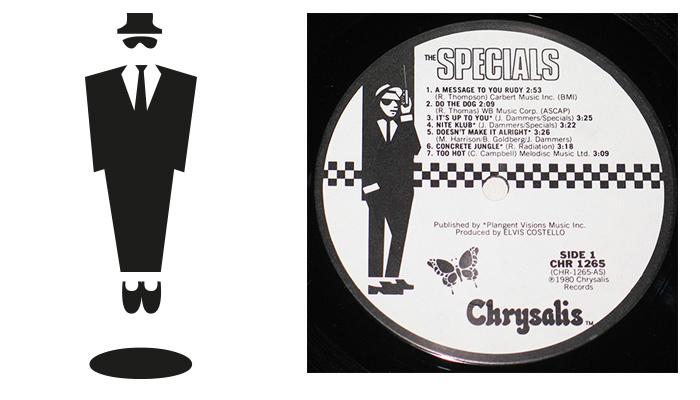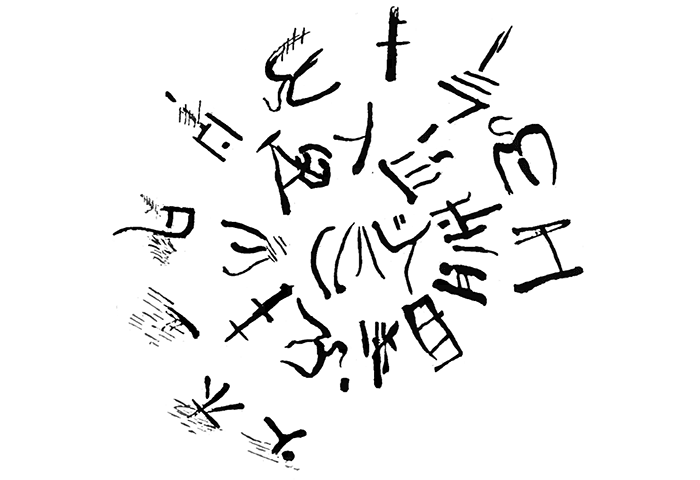
Vier Jahre nach der letzten Hauptversion erscheint mit der Version 7.0 nun eine weitere große Erweiterung des Schriftzeichen-Standards Unicode, die 2834 neue Zeichen mitbringt und den Gesamtumfang der kodierten Zeichen damit auf 113.021 Zeichen erhöht. Einige der neuen Bildzeichen in Unicode 7.0 sorgen in der Berichterstattung für Erheiterung. Zu diesen Zeichen zählen zum Beispiel:
»Stinkefinger« U+1F595
REVERSED HAND WITH MIDDLE FINGER EXTENDED»Vulkanier-Gruß« U+1F596
RAISED HAND WITH PART BETWEEN MIDDLE AND RING FINGERS»Schwebender Geschäftsmann« U+1F574
MAN IN BUSINESS SUITE LEVITATING
Die Auswahl solcher Zeichen wirkt auf Außenstehende nicht selten verwunderlich oder gar willkürlich. Doch hinter der Aufnahme neuer Zeichen stehen langwierige Abstimmungs- und Entscheidungsprozesse unter der Mitwirkung von Wissenschaftlern und nationalen und internationalen Normungsinstituten.
Der schwebende Geschäftsmann hat es übrigens lediglich aus Kompatibilitätsgründen in den Unicode geschafft. Die weit verbreiteten Piktogramm-Fonts Webdings und Wingdings wurden in den Unicode aufgenommen und damit auch der im Webdings-Font enthaltene, »schwebende Geschäftsmann«, der laut Aussagen der Zeichnerin Jen Sorenson eine Art Ausrufezeichen angelehnt an Plattencover der Band The Specials darstellen soll.
Neben weiteren Bildzeichen und neuen Währungszeichen für Rubel und den Aserbaidschan-Manat wurden auch 23 neue Zeichensysteme aufgenommen: Altnordarabische Schrift, Altpermische Schrift, Bassa-Schrift, Duployé-Kurzschrift, Elbasan-Schrift, Grantha-Schrift, Kaukasisch-Albanische Schrift, Khojki-Schrift, Khudabadi-Schrift, Linearschrift A, Mahajani-Schrift, Manichäische Schrift, Mende-Schrift, Modi-Schrift, Mro-Schrift, Nabatäische Schrift, Pahawh Hmong, Palmyrenische Schrift, Pau Cin Hau, Psalter Pahlavi, Siddham, Tirhuta und Warang Citi.
Mit 23 neuen Schriftsystemen ist dies die größte Anzahl neuer Systeme, die in einer Unicode-Version hinzugefügt wurden. Unicode 1.0 startete 1991 mit 24 Schriftsystemen. Die Erfassung aller Schriftzeichen der Welt wird also weiterhin konsequent vorangetrieben, auch wenn in der Berichterstattung der Fokus oft auf Piktogrammen bzw. Emoji liegt.
Die Linear-Schrift A der minoischen Kultur Kretas ist nun auch im Unicode vertreten
Noch fehlen entsprechende Fonts, die die neuen Zeichen aus Unicode 7.0 anzeigen können. Es ist jedoch damit zu rechnen, dass zumindest die neuen Symbole und Währungszeichen mit den nächsten größeren Betriebssystem-Aktualisierungen in Systemfonts aufgenommen werden.